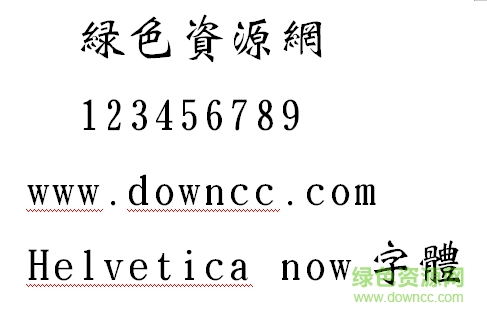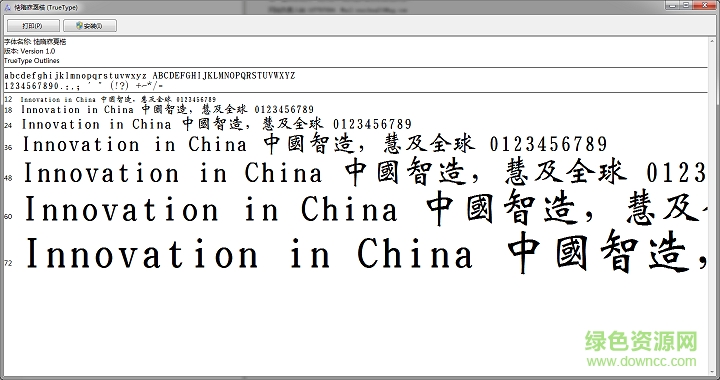
文鼎魏碑繁是文鼎字體庫(kù)中的一款魏碑繁體字體,筆畫(huà)偏粗,字形略圓,藝術(shù)設(shè)計(jì)會(huì)常用的。還適合用在多個(gè)不同領(lǐng)域,有需要的用戶(hù)趕快來(lái)下載體驗(yàn)吧!
筆意樸拙,不避鋒芒,規(guī)則中正
其風(fēng)格蒼勁堅(jiān)實(shí)
適用于文化類(lèi)的宣傳設(shè)計(jì)
結(jié)構(gòu)跌宕起伏
以及商業(yè)類(lèi)品牌的廣告和產(chǎn)品包裝設(shè)計(jì)